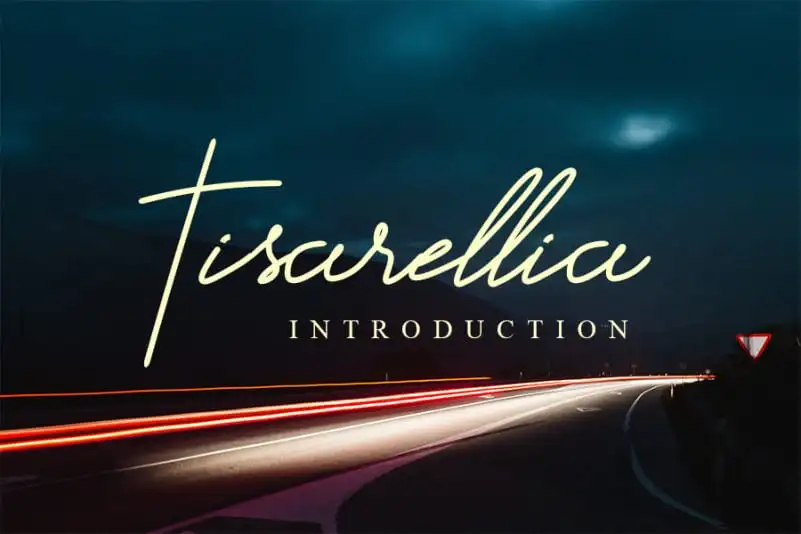
Tisarellia Handwritten Font – Download Grátis
Tisarellia é uma elegante fonte escrita a lápis que mantém seus influentes traços serifados ao mesmo tempo contemporâneo e fresco. Perfeita para aqueles interessados em personalizar seu trabalho de design, esta fonte atinge desde os cartões de visita até as bordas das páginas, combinando clássico com modernidade sem perder nenhum dos dois. Com sua versatilidade, Tisarellia é perfeito tanto para designers criativos que querem dar um toque único a seus projetos quanto para quem está em busca de uma opção mais sofisticada e profissional. Ideal tanto para aplicar em cartazes e nomes destacados quanto para estilos de folheto, esta fonte tem o poder de transformar qualquer projeto em algo único e memorável. Em um mundo onde criatividade é tudo, Tisarellia Handwritten Font promete ser uma peça fundamental no seu arsenal de recursos de design.